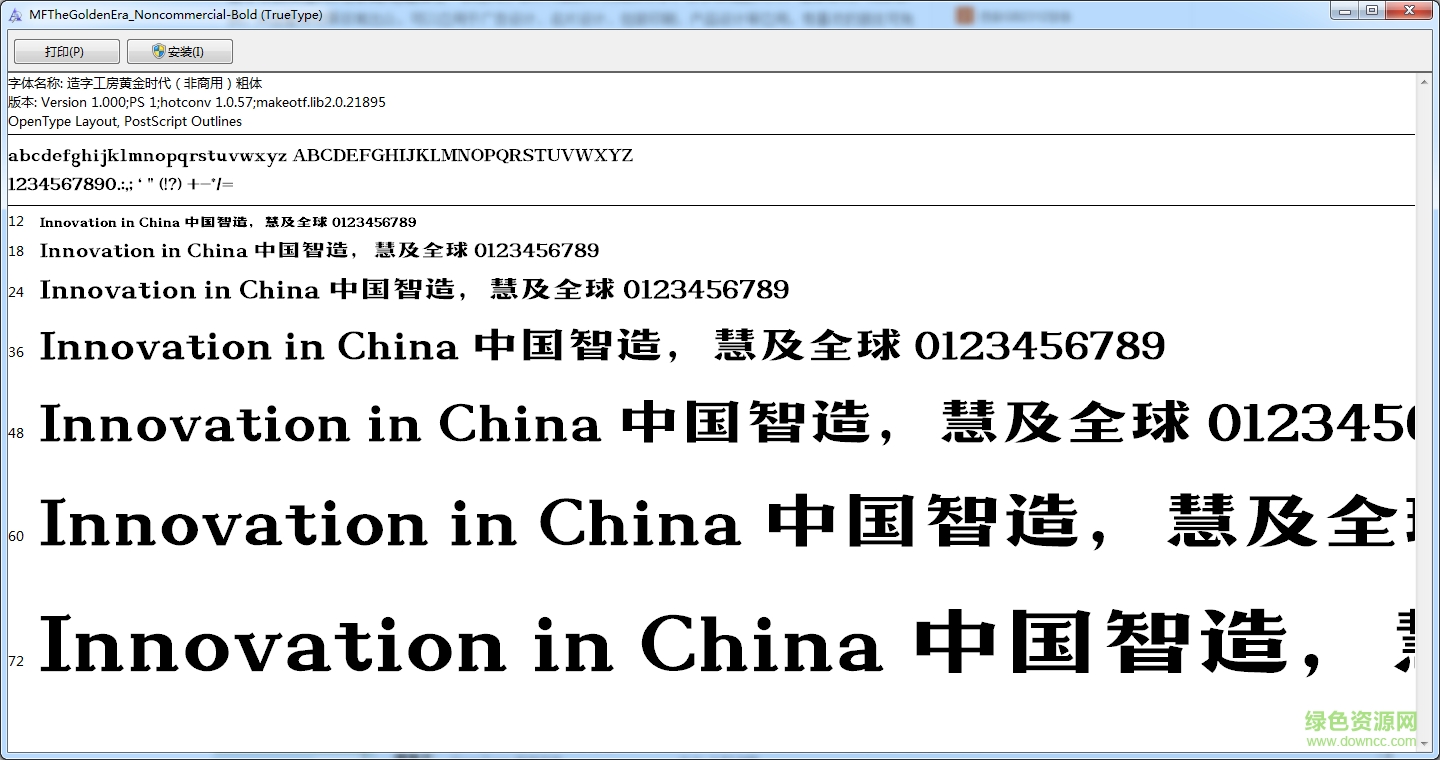
mfthegoldenera是什么字體?mfthegoldenera_noncommercial字體又叫造字工房黃金時代,包含了所有的常用字符,筆畫舒展,線條過渡流暢,表現(xiàn)力非常強,歡迎大家免費下載!
造字工房黃金時代體,由造字工房為《黃金時代》電影定制字體,結(jié)合影片時代特征,以及主人公蕭紅所處的年代環(huán)境而設(shè)計。
其結(jié)構(gòu)嚴謹,整體風(fēng)格厚重典雅,筆畫飽滿舒展,耐人回味。適用于電影字幕、文字標題、廣告設(shè)計等視覺環(huán)境,有著極強的應(yīng)用空間。